Um sotaque Russo para a SporTV
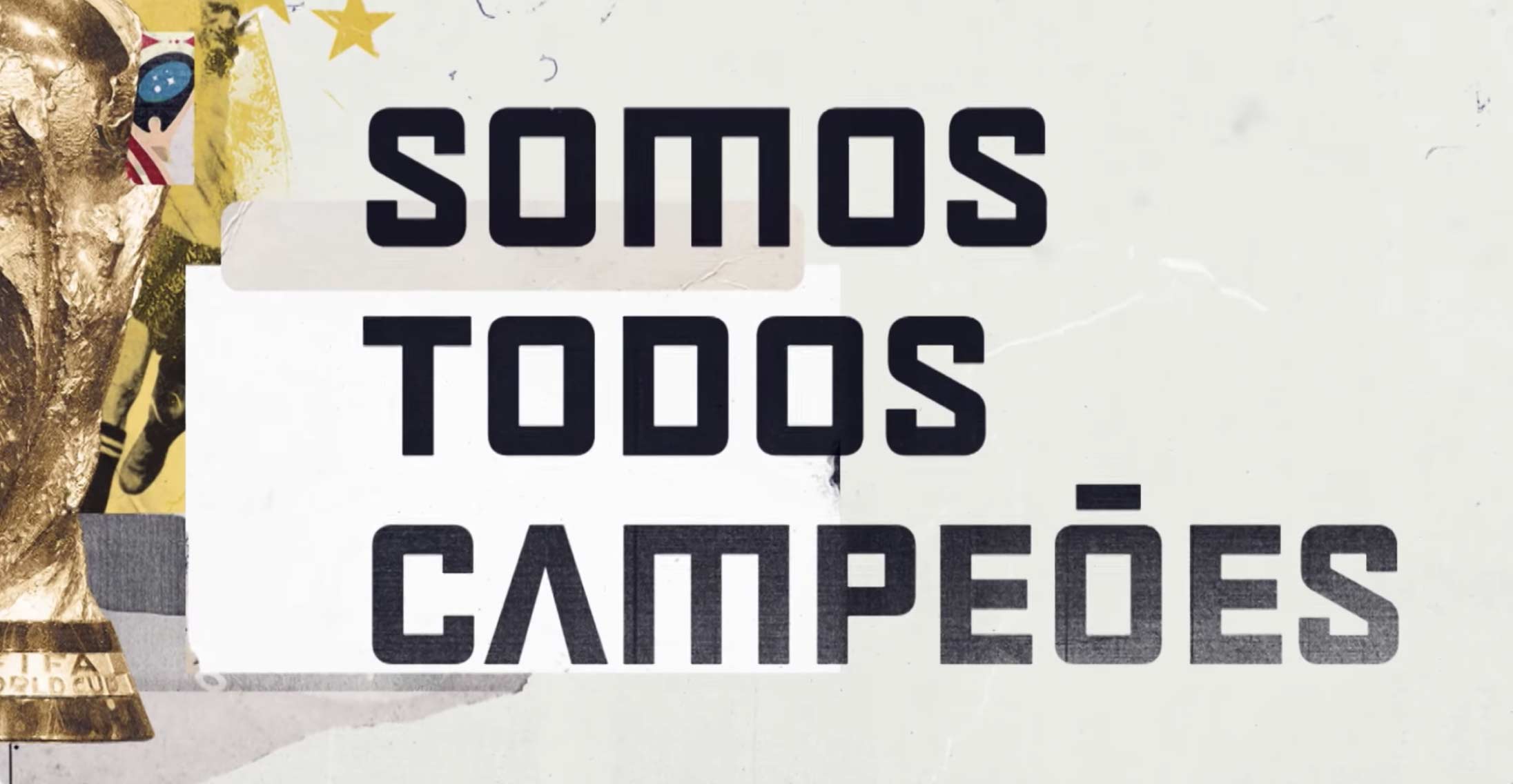
Um dos mais belos aspectos da Copa do Mundo é a integração entre diversos países em torno de uma mesma paixão. Há um intercâmbio cultural espontâneo que traz surpresas, descobertas, memes (é claro), mas também homenagens. Durante a Copa do Mundo de 2018, a fonte da SporTV adotará um sotaque orgulhosamente Russo.
A tipografia exclusiva, desenvolvida pela Fabio Haag Type em colaboração com a equipe de Comunicação & Branding da Globosat, é um elemento central da campanha SporTV Sou Na Copa, que contou também com o talento da Firmorama.
O alfabeto utilizado na Rússia tem muitas semelhanças com o nosso, afinal, o Cirílico – assim como o nosso Latino – descende do mesmo ancestral, o alfabeto Grego. Encontrar formas semelhantes aos dois foi o ponto de partida para expressar a integração destes dois mundos, com atenção para preservar a essência da linguagem visual própria da SporTV.
Há ousadia nas formas geométricas simplificadas. Há irreverência nas letras espelhadas… há uma festa, afinal, há uma Copa do Mundo \o/